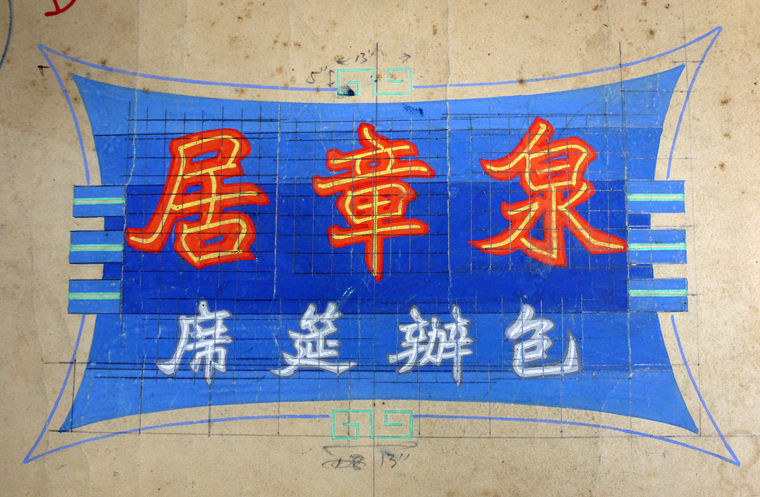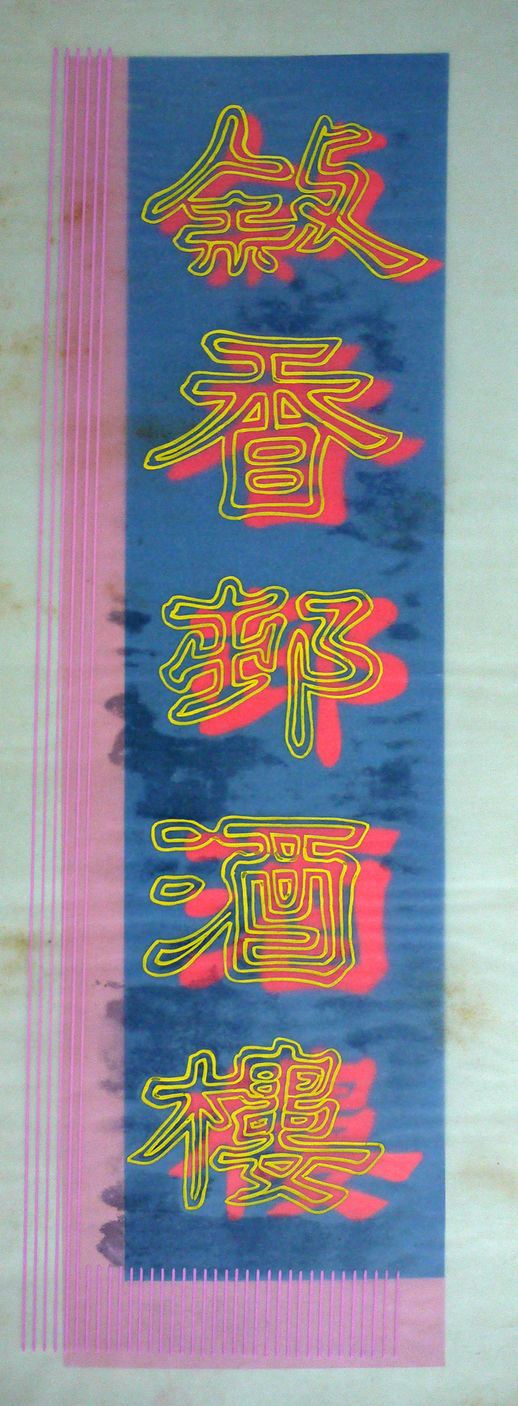
沟通的建筑:香港霓虹招牌的视觉语言谭智恒
有说要知某城市有多繁荣富庶,且看她入夜后有多光亮。到过香港的游客,壮丽的夜景必定在心中留下深刻的印记。自五十年代起,「东方之珠」这称谓就成为了香港的同义词。生动活泼的霓虹招牌,令人联想起种种浪漫情怀,是「东方之珠」称号的代表符号。霓虹招牌勾勒出香港的街道和社区,为城市注入动力。夜幕低垂,充满生气。
文字和视觉符号无处不在,渗透香港每个角落,蔚为奇观。大量的中英文视觉信息,偌大规模,风格迥异,五光十色,以不同物料制作、不同潮流展现,揭示了此地的能量与精神。这些符号代表了我们的身份和美学气质,也可窥见人们在这地球一隅的生活方式与文化。这就是香港。
霓虹招牌的制造技术早在上世纪三十年代引入香港,但直到了二战后,香港经济快速复苏,霓虹招牌才得以茁壮成长。霓虹招牌是推广各种商业活动的不二之选,大量用于各行各业如餐厅、百货公司、戏院、酒吧、夜总会、桑拿浴场等。具有强大消费力和闲暇时间的客户层不断增长,商户间的竞争越演越烈。霓虹招牌不但成为商家宣传业务的必争之地,也成为香港经济与旅游业发展的有力象征。
招牌与香港的街道景观
1977年,建筑师Robert Venturi、Denise Scott Brown和Steven Izenour发表了一篇建筑研究,题为《向拉斯维加斯学习》(Learning from LasVegas)。当时建筑界由现代主义思想主导,而Venturi等人的研究开创先河,探讨的本土建筑,其定义并不是建筑物的实体,而是空间里的文字与视觉沟通元素,换言之,建筑就是符号。Venturi等人写道:「[拉斯维加斯]的建筑风格与符号是反空间的,是以沟通凌驾空间的建筑;空间建筑与景观上的元素由沟通主导。」1这种以沟通主导的「反空间」建筑概念,最佳例子就是一栋栋单调乏味的盒子楼宇,它们通常离道路有一段距离,并远离途人和车辆。在七十年代以汽车主导的拉斯维加斯来说,人事活动隐藏于千篇一律的建筑中,需要更大更夸张的招牌,以求引人注目,并增强「地方感」。
1970年代拉斯维加斯的霓虹招牌
相比六、七十年代的拉斯维加斯,香港的都市建筑发展走上颇为不同的道路。香港的人口密度比前拉斯维加斯高得多,而建筑与都市规划倾向以行人为中心,以多用途和垂直发展为本。行人经常与车辆擦身而过,店铺盘踞着地面及不时占据以上几层楼面,而基座以上则往往商住兼用。香港建筑师兼城市规划师Peter CooksonSmith仔细检视过香港有机与即兴的街道文化,以及视觉沟通如何成为独特文化身份的一大元素。Smith写道:「层层叠叠的招牌、种种琐碎的细节和与人沟通的装置,让乏味的街景变得统一而充满乐趣。这种统一感并不是来自较正统的、以形式化重复建筑元素来建构的建筑方法。」2Smith认为即兴与凌乱带来的发展与变化,大胆地颠覆了原有的建筑构架。这种「附加」方式,表现在香港人大胆创新地运用招牌作招徕,寄生于楼宇上。「消费的图象经实际与比喻的方式运用起来,组成了街道的语言,并凭着在对立时的主导地位,表明一种象征性的身份。」
书法与招牌
这种独一无二的高密度城市景观,源自把书法艺术融入建筑的中国传统,历史悠久。垂直的对联、横向的匾额、墙壁和石碑上的镌刻等,数千年来装饰着庙宇、住宅、公共场所等的门户和厅堂。身兼艺术家、诗人与作家的蒋勋这样形容书法在中国建筑里的重要性:「书写线条与建筑物的功能性质配合,事实上,书法也已经是建筑设计美学重要的一部分。」4书法既具识别功能,亦具艺术的目的,通常由文人雅仕或书法家挥毫,然后予工匠雕刻。虽然霓虹光管招牌是舶来品,但中国招牌的传统却得以保存,且融合到本土霓虹招牌的视觉语言中。放大了尺码与跨张了的视觉效果,更能反映日新月异的城市肌理和建筑特色。香港文化评论人胡恩威就中文字在混合用途楼宇的角色这样写道:「混合用途建筑之所以是香港风格的奇景,是因为建筑物与文学产生的化学作用,建筑物的外墙被文字包围着,功能上文字成为空间用途的代号,让街上的途人能够阅读和知道个别单位的功能和用途。这些文字的组合、字款的设计,为平平无奇的石屎建筑带来了一种充满动感和活力的景象。」
虽虹光管招牌是舶来品,但中国招牌的传统却得以保存,且融合到本土霓虹招牌的视觉语言中。放大了尺码与跨张了的视觉效果,更能反映日新月异的城市肌理和建筑特色。
在实用层面上,招牌能提供环境导向指示,帮助人们寻找及识别地方和活动。不管是霓虹或其他类型的招牌,都可以和建筑物合而为一或者成为建筑物的延伸,为单调乏味的楼宇和社区赋予身份与个性。安装招牌的初衷或许是因为功能上的需要,却成为代表着人事活动、生活方式和本土文化的一种象征。有些招牌特别为远处观看而设,有些则让人从较近的距离观看,视觉要求有所不同。除了一些放在店面、尺寸较小的霓虹招牌外,大部份霓虹招牌的设计都能让人立即辨认和看懂,而且大多安装在较高处让途人仰望。霓虹光管十分明亮,不管是安坐在驶过的车辆抑或在悠闲漫步的人都能轻易地看到这些招牌。霓虹招牌的主要功能不是为附近环境提供照明,而是吸引途人注意光源本身,当中的视觉信息既在招牌中也关于招牌本身。换言之:媒介即是信息。
招牌招牌景观分析构架
虽然香港的招牌经常给人不拘一格的混乱感觉,但当仔细观察下,招牌如何在城市中展现却有一套基本的模式。笔者将各类型的招牌与楼宇、行人和城市环境之间的互动,建立了一套分析构架,代表了十二种出现在香港城市中的招牌原型,并根据它们安装在楼宇的三种位置,分成在建筑物上伸延、在建筑物外墙以及在店面这三大类。这些种类的招牌以不同的方式重复出现,遍及城市各处。借着此分析构架,我们能更深入地理解招牌的各范畴,包括视觉表现、字体、设计、美学价值、内容要求、建造模式、观看距离、与城市的互动等。
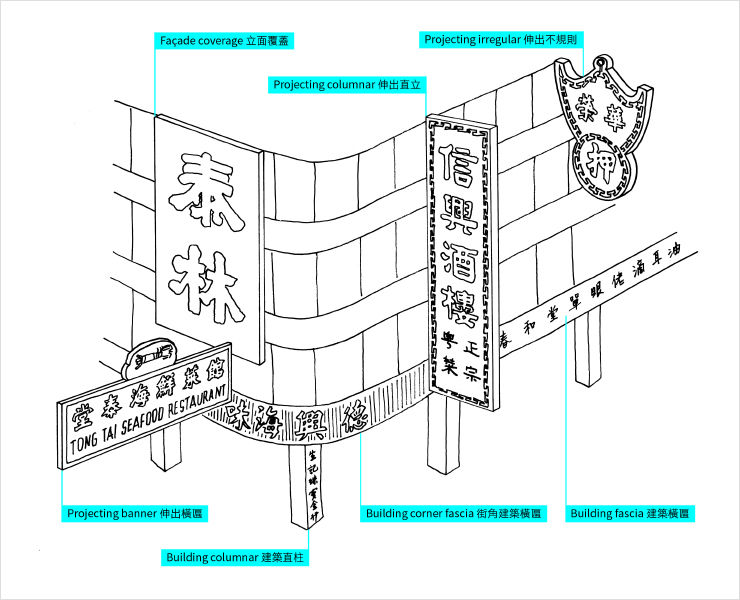
香港招牌景觀分析框架:街角建築物
香港招牌景觀分析框架:橫切面
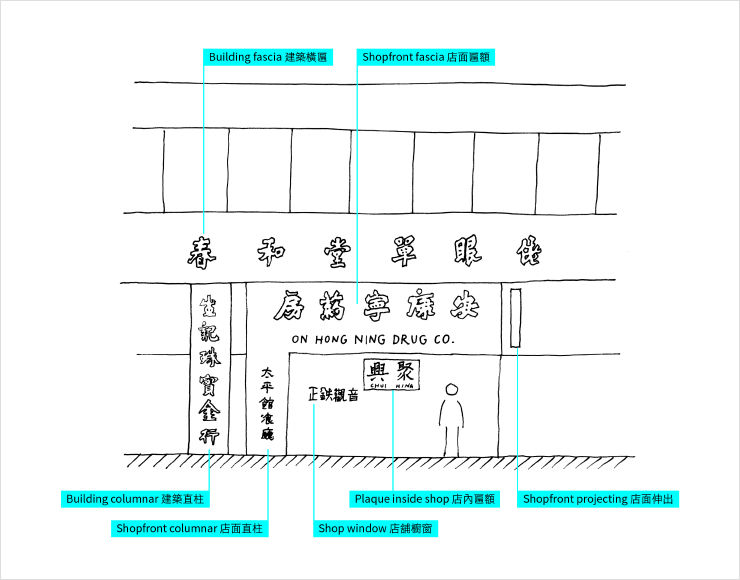
香港招牌景观分析框架:立面
伸延的霓虹招牌
上述十二种招牌或会以霓虹方式呈现,但霓虹光管大多用在伸延式招牌上。这种招牌以钢架与钢线安装在楼宇上,是建筑物的延伸物,从楼宇的外墙伸展出来,与楼宇和路面成垂直角度。
伸出直立式招牌是香港霓虹招牌中最有代表性的,不仅继承了上世纪三十年代开始出现在北美各地城镇的戏院霓虹招牌的特色,还发扬了中国的楹联传统。中文以垂直和水平排列也能阅读,反之,英文字母垂直排列时则较难阅读,并影响视觉效果,因此中文的直立式招牌比起英文版本更为协调。这些招牌从高楼大厦旁伸展出来,跟来往的车辆和行人成垂直角度,非常显眼,倍觉震撼。直立式招牌常见于主要街道上,或楼宇的狭缝间,身处数百米外也能轻易地看见,看起来像悬浮在夜空似的。
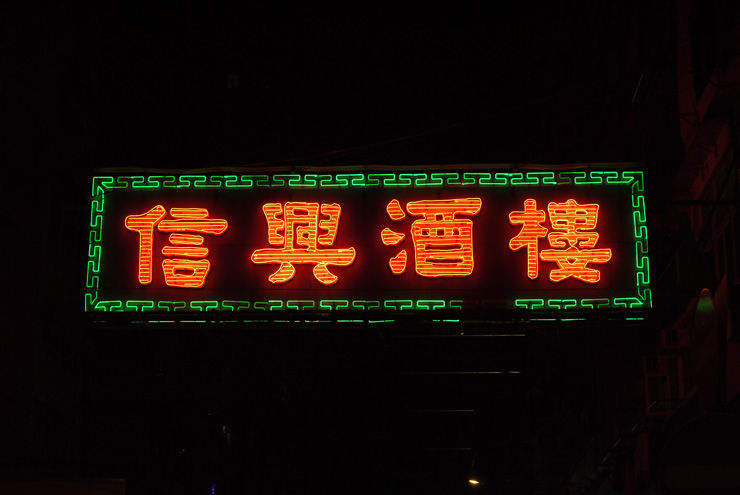
信兴酒楼(深水埗)
简约的伸出直立式招牌,敦厚的隶书配以中式边框。
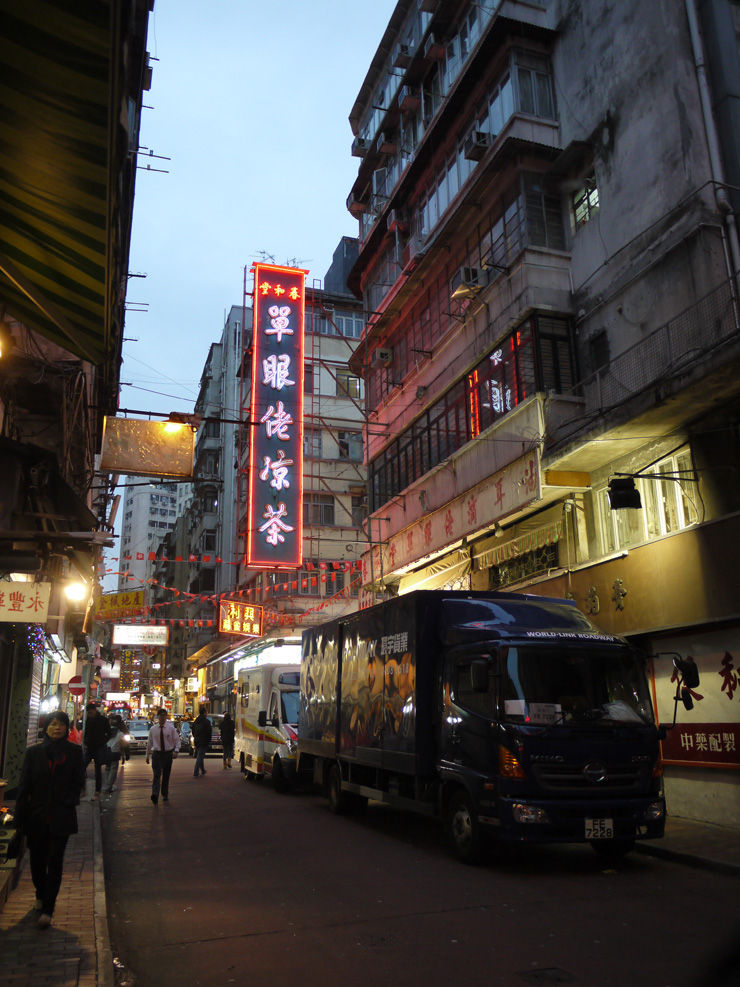
单眼佬凉茶(油麻地)
此简洁的伸出直立式招牌,几个街口外也清晰可见。
伸出直立式招牌的最基本结构是简单的直立长方形柱,四边围着边框,通常由双行线组成,也有装饰性的边框,好让招牌在复杂的闹市背景中突显出来。柱的形状除了长方形外,也有梯级状、绽放状、曲线状和其他不规则形状,上世纪中期十分流行,也是向装饰艺术风格(Art Deco)传统的致敬。招牌的背景有素净的,也有几何图案或平衡线的纹理。
柱的顶部在此称为「冠」,通常以商户的标志或图案装饰。例如珠宝店的招牌常以光管构成闪亮的钻石来推广生意,专营盐焗鸡的客家酒店亦喜爱在招牌上画上整只盐焗鸡。也有招牌用上吉祥物,例如鹿园餐厅的招牌用上一头鹿。这些图象元素都是以简单线条画成,具有标志性意思,让人一目了然。
大金龙麻雀耍乐(湾仔)
此伸出直立式招牌尺寸虽然不大,设计却甚为华丽。招牌冠以龙头,龙身包裹着整个招牌,底座为一朵白云。
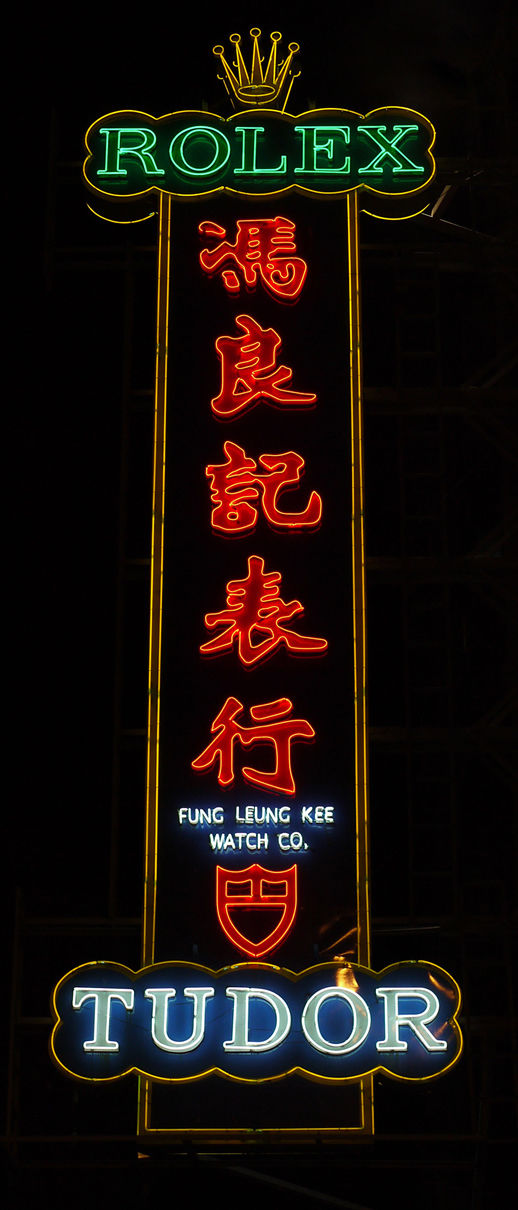
冯良记表行(湾仔)
大型伸出直立式招牌,矗立于香港岛电车路上,甚为显眼。手表品牌名字占据了冠部和底座,而英文店名则极为细小。
柄的底部有时候会加上个宽阔的「底座」,用以写上店铺的英文名称或以其他中英文标语。跟招上其他字比较,底座的字体通常细小得多,不过因为居于较矮位置,底座的字体是让人在较近处看的。招牌设计在双语处理上较偏重视觉元素较突出的中文,用以吸引本地客户,但对不谙中文的人仕也能发挥如地标般的作用。
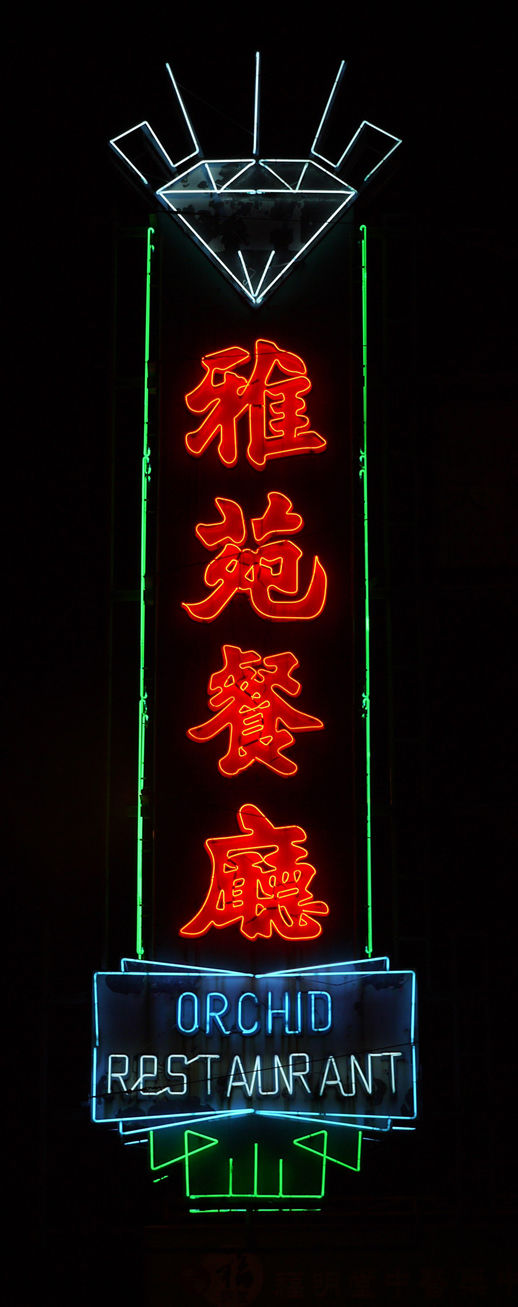
雅苑餐厅(湾仔)
一家西餐厅的伸出直立式招牌,顶上冠以一颗闪亮的钻石,底座为餐厅的英文名称。钻石显然不是餐厅名字的象征,也非代表业务的范围。
从楼宇伸出来的悬臂式招牌也有横向的,当中有不同的比例与高度。有些横匾会延伸至马路上离楼宇颇远的上空,以配合信息的长度并尽量显眼。跟伸出直立招牌比较,横匾的设计方便人在近处辨认,特别是那些安装在较矮处的。有些横匾也拥有带图象元素或标记的标志,有些横匾底部附加了「栏标」,上面写上该门生意的英文名字或标语。
永兴大药房(佐敦)
伸出横匾式招牌,下方附以栏标。
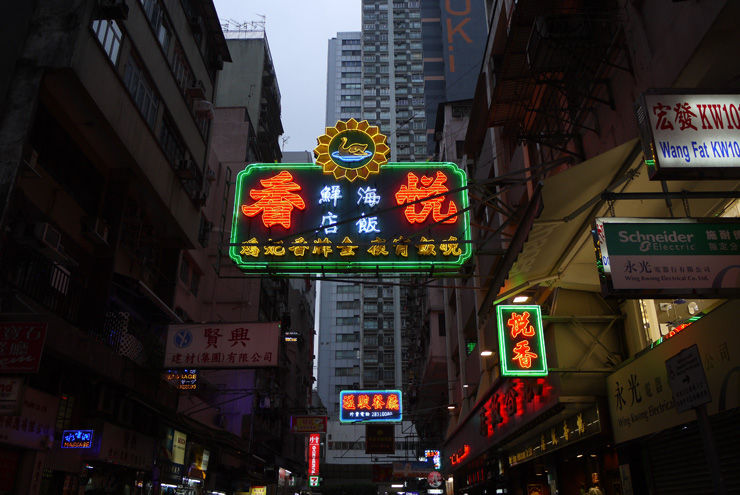
悦香酒店(湾仔)
此酒店位处横街,伸出横匾式招牌冠以盐焗鸡的图象,为该店的招牌菜。
伸出式招牌也有形状不规则的,例如皇后大道西森美餐厅的霓虹招牌用上牛的形状,让人知道餐厅专营牛排。中环罗富记粥面专家的招牌用上鱼的形状,代表着驰名的鱼粥。此外所有的当铺都用上蝙蝠与金钱形状的招牌,以代表财运,而「押」字与当铺的名字也融汇于在图象中。招牌的形状成为与别不同却又易于辨认的符号,在闹市中特别显眼,让人很快就认得出来。
同德大押(湾仔)
传统蝙蝠与金钱当铺招牌。
皇都桑拿(北角)
伸出不規則式招牌,頂上冠以皇冠,為商號的象徵。
太平馆餐厅(铜锣湾)
伸出不规则式招牌,顶上冠以餐厅的标志。留意中文店名由右至左阅读,英文则由左至右。
各商户联手令主要街道如弥敦道的招牌看上来和谐协调,这情况在香港没有可能发生。现实情况可能刚刚相反:在这竞争极度激烈的环境中,各商户的招牌都设法比对手更大更亮。有趣的是,从前每块招牌的安装大都十分礼让,不会刻意互相遮盖,招牌之间总会保持合理的距离。林林种种的直立与横匾招牌不仅有实际的作用,还意外地营造了错落有致的效果,充满层次和活力。这种有机的发展可说比所有刻意的规划或立法都还要有效,也象征着香港人的原创精神。
建筑物外墙的霓虹招牌
霓虹光管也会用于楼宇的外墙上,让马路对面的途人或乘车经过的人都能看到。这些招牌的形状大多反映了建筑物的形状或结构:横向(建筑横匾)、纵向(建筑直柱)、包围在位于十字路口的建筑物的角位(街角建筑横匾)、覆盖整块外墙连窗户(立面覆盖)。
就立面覆盖招牌而言,整块外墙或建筑物本身也有效地转化成为显眼的地标,令人留意到该建筑物。例如昔日在弥敦道售卖电器的泰林无线电有限公司,招牌就覆盖整栋六层高的建筑物外墙,招牌上的两个中文字每个大约六麦克尔,采用隶书字体设计。
店面的霓虹招牌
就街道水平的招牌而言,途人跟商店距离十分接近,霓虹光管的角色较不重要。如果用上霓虹招牌,尺寸通常较小,以吸引潜在顾客的注意,让他们走进店内。在某些社区里,传统商用楼宇的突出部份会伸延至行人道上,商铺的招牌大小乃取决于楼顶的高度跟行人的距离,霓虹招牌通常用在楼顶较高的店铺上,好让街道对面的人也能看得到。
霓虹招牌通常会有个由金属片制造的底座,再把光管安装在底座上。图文以金属片立体模造或切割出来,然后焊接到底座上,再喷上颜色。有些字体和图案轮廓会焊上凸起的边坑围起霓虹光管,令图案及笔画更加清晰。底座的颜色选择通常跟霓虹光管有异,好让招牌在日光下和夜间亮着时的风格略有不同。
正如本文所述,霓虹与其他种类的招牌塑造着香港的城市经验:不单透过视觉语言,而且也与建筑、城市肌理和人们的生活互动。这种「沟通的建筑」,不管如何兼收并蓄、随性而行,背后总有其模式,对观看功能有所要求,而衍生了其视觉表达形式。霓虹是一种可塑性高的媒体,在香港不但承传了其北美故乡的美学上特质,还继承了中文书法的丰富传统,调节本地环境,这都要多得本地一群大胆创新的霓虹工匠和设计师。凡此种种,为香港带来独一无二的本地视觉文化,创造出今天我们所认识的城市经验,难忘且意义深远。
过去十多年,香港霓虹招牌的数目持续下降。霓虹招牌发放的柔和灯光,一度为街道营造了浪漫得近乎超现实的景观。时光荏苒,此景观渐渐被巨型广告牌取代,明目张胆地鼓吹全球化与无节制的消费主义,我城从此面目全非。从前,五花八门的霓虹招牌,代表着独立经营、风格迥异的个体小商户,如今已渐渐被连锁店与国际品牌取代。新的招牌往往是了无生气的巨型喷画海报,上面满是超写实的人像与消费品,覆盖着建筑物的整堵外墙,在泛光灯照耀下,昼夜不分,没留下半点想像空间。
本文的精神并不是哀叹一门「逝去的艺术」或怀缅一段辉煌的历史,而是希望清楚地理解霓虹及其他形式的招牌在香港的价值与意义,好让我们薪火相传,将之升华、重新诠释、推往新的层次。希望本文可牵引更多的讨论,引起公众欣赏并保存本土招牌的视觉文化。